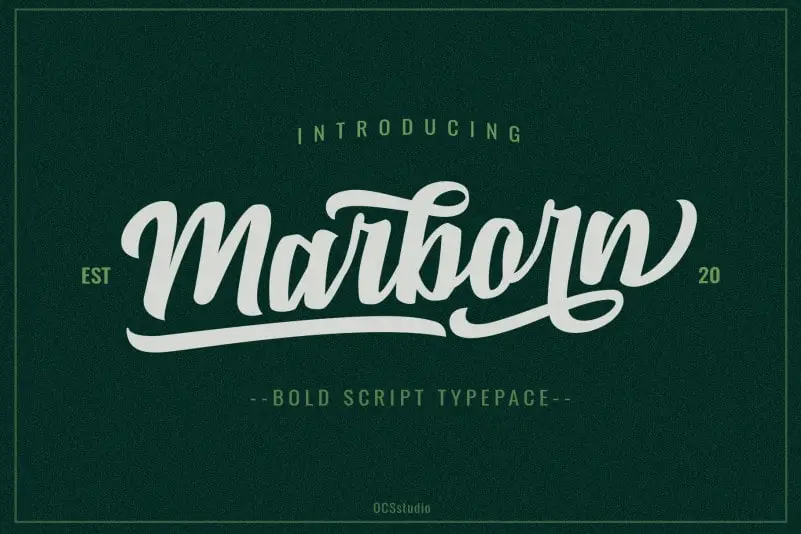
Marbrorn Script Font – Download Grátis
A ‘Marbrorn Script Font’ é uma escolha perfeita para designers que buscam adicionar um toque único a seus trabalhos visuais. Conhecida por sua moderna e elegante aparência, esta fonte script foi projetada para atender às necessidades dos mais variados projetos de design. Seja para criar um logotipo atrativo e inovador, produzir camisetas personalizadas com rótulos atraentes, estilizar mensagens de mídia social, até mesmo desenhos gráficos em mugs ou sacolas de mercado – esta fonte é versátil o suficiente para atender a uma ampla variedade de necessidades. Ideal tanto para aqueles que valorizam um design claramente criativo quanto para os designers mais tradicionais, a ‘Marbrorn Script Font’ oferece uma combinação perfeita de elegância e sofisticação, sem deixar de lado o encanto do script. Para designers que procuram uma fonte versátil para inúmeras aplicações, esta é uma ótima escolha.